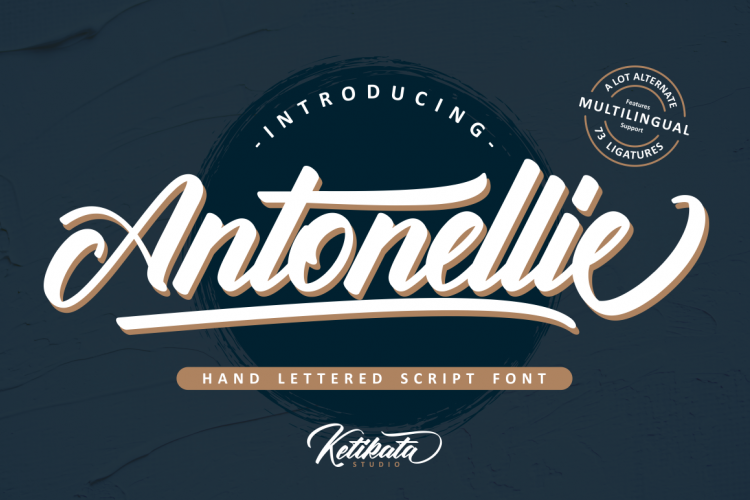
A Antonellie Calligraphy Font é uma escolha perfeita para quem busca um estilo elegante e sofisticado. Esta fonte Script Moderna foi cuidadosamente criada através do desenho manual de letras, oferecendo várias alternativas estilizadas e círculos especiais que permitem a criação de design personalizado. Suas linhas fortes e bold tornam-a uma opção ideal para logotipos (logotypes), projetos de marca e muitas outras necessidades de design, como cartões de visita, embalagens, materiais promocionais e mensagens. Esta font é perfeitamente adaptada para criar um impacto forte em qualquer projeto que exija uma gravação cuidadosa. Ela combina a força e o poder das letras cursivas com a elegância do estilo atual da escrita manual. Para quem deseja experimentar esta fonte antes de comprar, Antonellie Hand Lettered Script é uma ótima opção para começar. A M.0Type trouxe esta fonte moderna que se destaca na categoria de script, oferecendo-lhe um design personalizado e único.